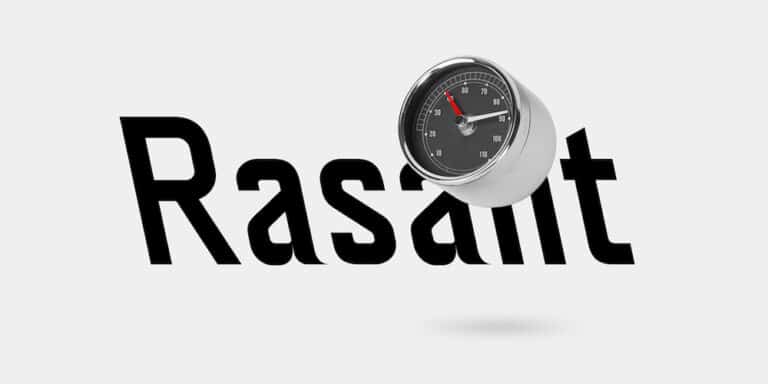
Serifenlose neue Rasant
Bei der Foundry neue erschien jetzt eine Schrift, deren strenges Raster nur wenig Platz für optischen Ausgleich lässt.
neue Rasant taufte Typedesigner Alexander Roth seine Schrift, sie ist die Interpretation einer Type, die von der Singapore Land Transit Authority für ihre Beschilderung verwendet wird. Das Schriftdesign basiert auf einem strikten Raster mit wenig bis keinem Spielraum für optischen Ausgleich oder jegliche Art von Harmonisierung.
neue Rasant ist uniwidth, das heißt ein Buchstabe ist in sämtlichen Schnitten gleich breit, das a in Light beansprucht also genauso viel Platz wie das a in Bold. Sehr praktisch, wenn man schnell einen Schriftschnitt austauschen will, ohne dass gleich das ganze Layout zusammen bricht.
Schriften, in denen ein Buchstabe in allen Schnitten gleich breit ist nennt man Uniwidth, Multiplex oder Duplex Fonts.
Die Kursive gibt es nach rechts und links geneigt.